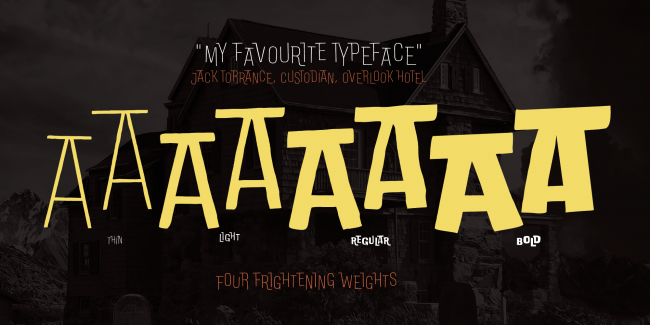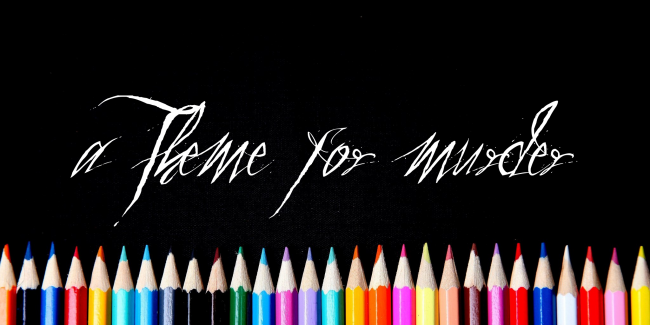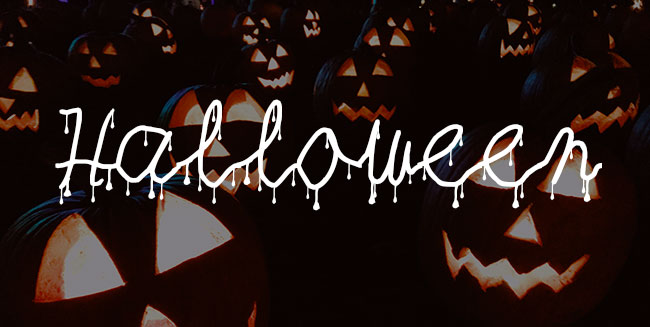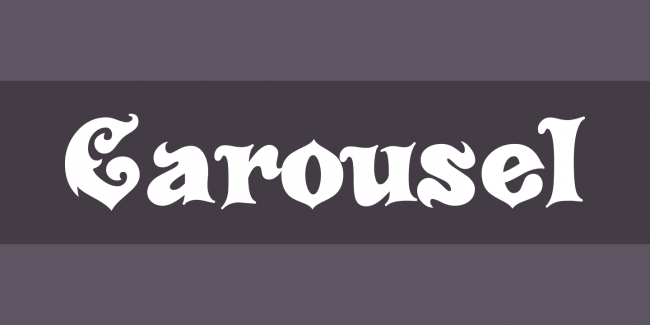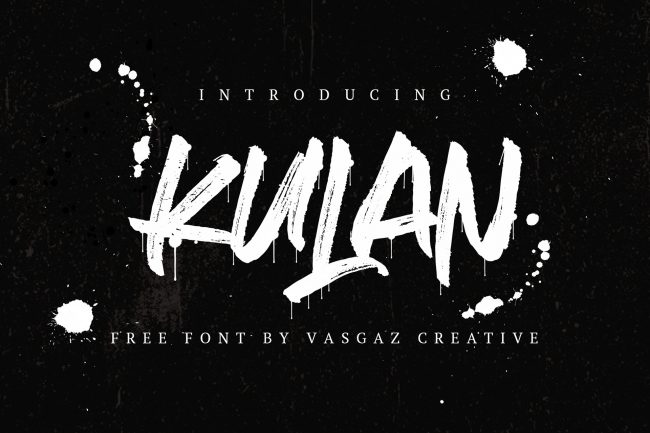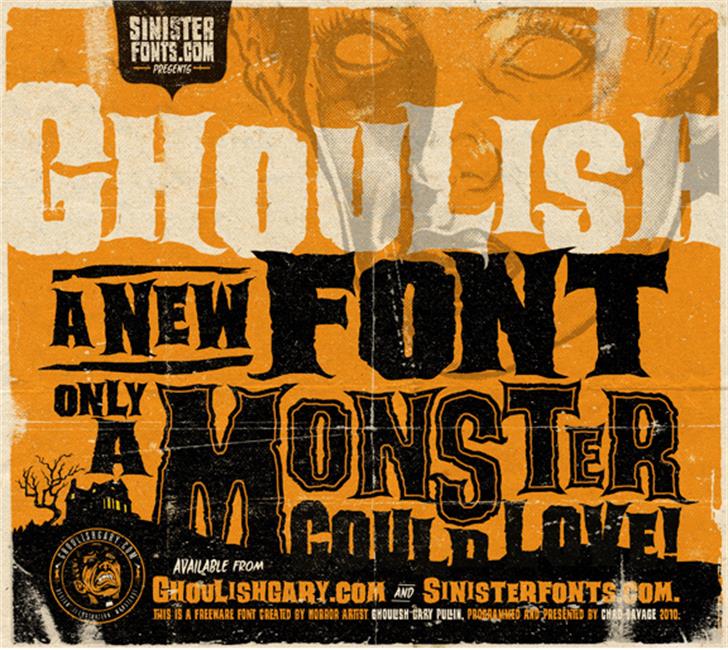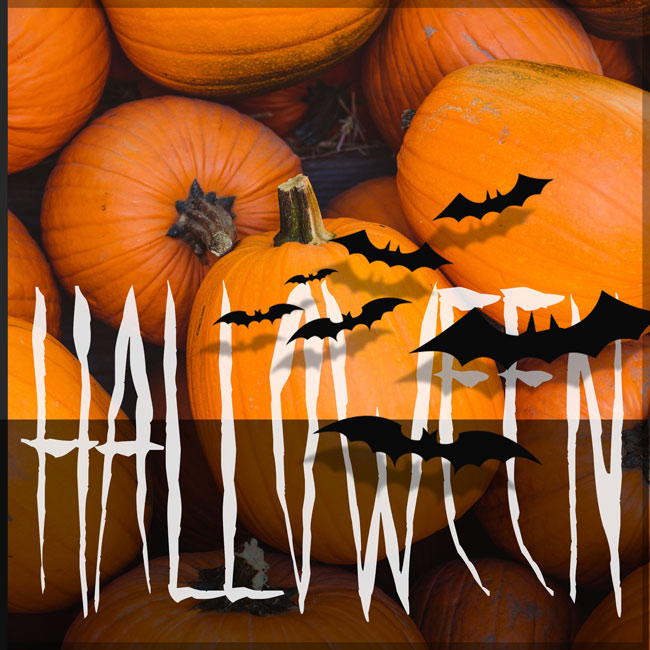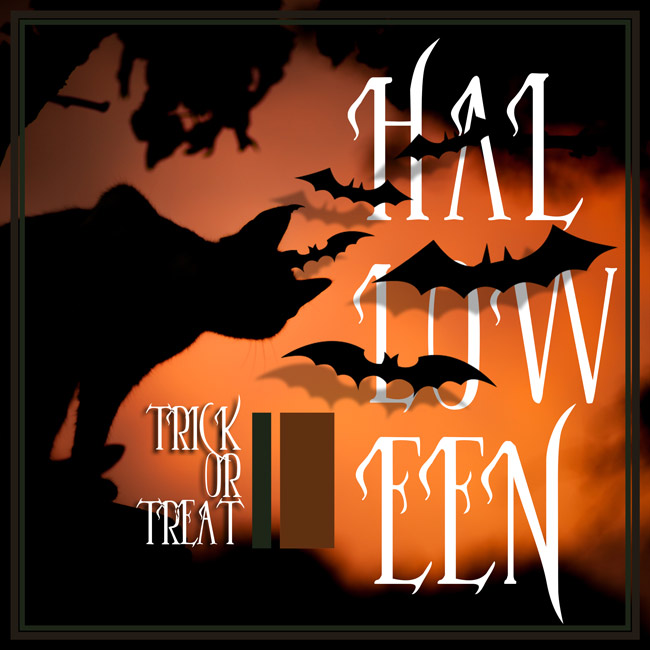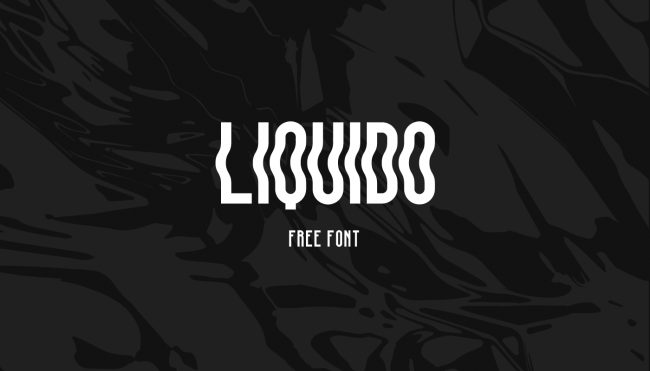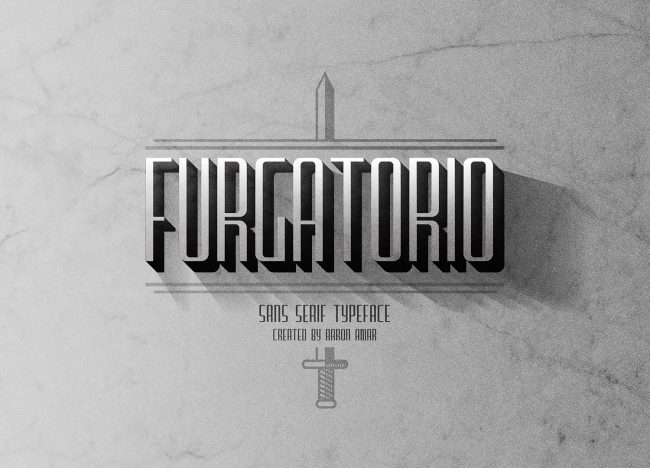
20 typographies pour Halloween à télécharger gratuitement
Halloween se rapproche très vite !
C’est le moment pour harmoniser vos contenus et vos visuels avec des typographies stylisées et adaptées.
Nous vous proposons aujourd’hui une sélection de 20 typographies gratuites spécialement dédiées à Halloween pour parfaire la création de visuels délicieusement monstrueux 😉
1. Spooky Halloween
2. Spirit Halloween
3. Carousel
4. Dissonant
5. The Truth Will Out
6. Dark & Black
7. October Crow
8. Yataghan
9. A Theme For Murder
10. Kulan
11. Furgatorio
12. Alcotton font
13. Liquido
14. DoubleBass
15. Evilution – Horror Typeface
16. HeadHunter
17. Raven Song
18. Almost Dead
19. Ghoulishhalloween typographie superbe pour graphiste
20. Parlestongue